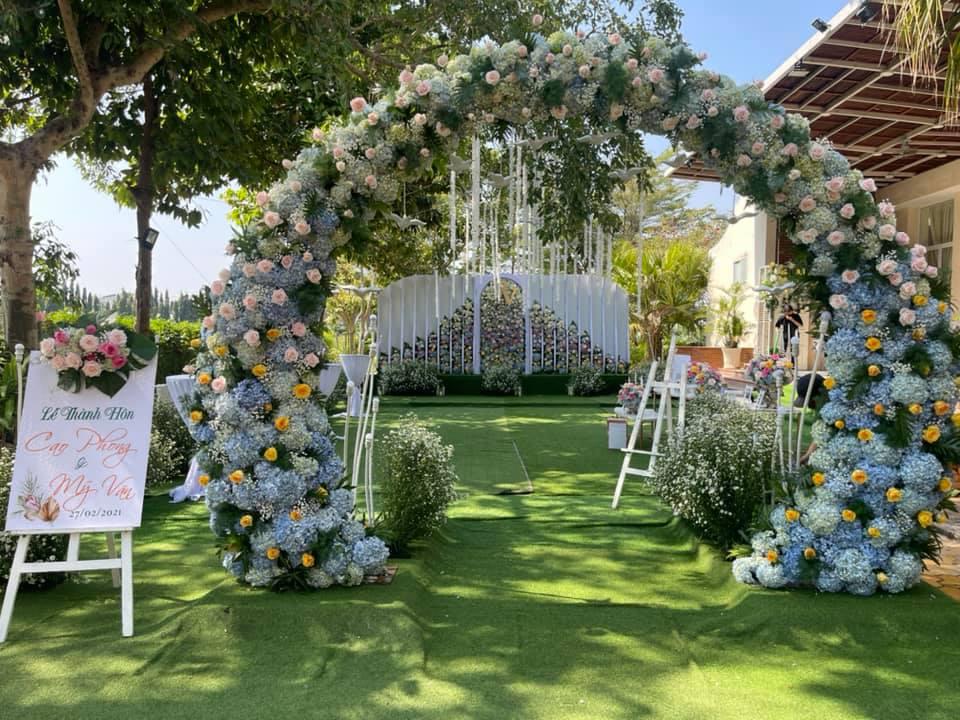
Font VNI - Khám phá và tải về bộ sưu tập font VNI đa dạng dành cho máy tính
Bộ sưu tập font VNI với hơn 300 kiểu chữ đa dạng, bao gồm font VNI thư pháp, VNI wedding và nhiều phong cách khác, thuộc bảng mã VNI. Hỗ trợ tiếng Việt hoàn hảo với nhiều định dạng và kiểu chữ độc đáo. Để sử dụng, bạn cần các công cụ hỗ trợ gõ tiếng Việt như Unikey hoặc Vietkey.
Khám phá một số định dạng và kiểu chữ độc đáo trong bộ sưu tập font VNI.